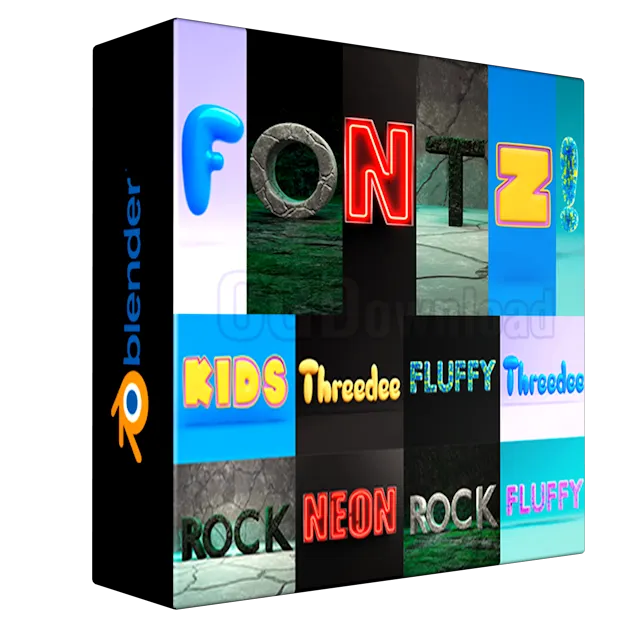
FONTZ Free — Various 3D fonts
FONTZ Free — Various 3D fonts — эти мультяшные 3D-шрифты можно легко использовать в своих проектах (посты в социальных сетях, листовки, веб-дизайн, дизайн мобильных приложений, можно использовать в качестве аватаров и т. д.). Благодаря исходным файлам вы можете играть с 3D-шрифтом и получать удовольствие!